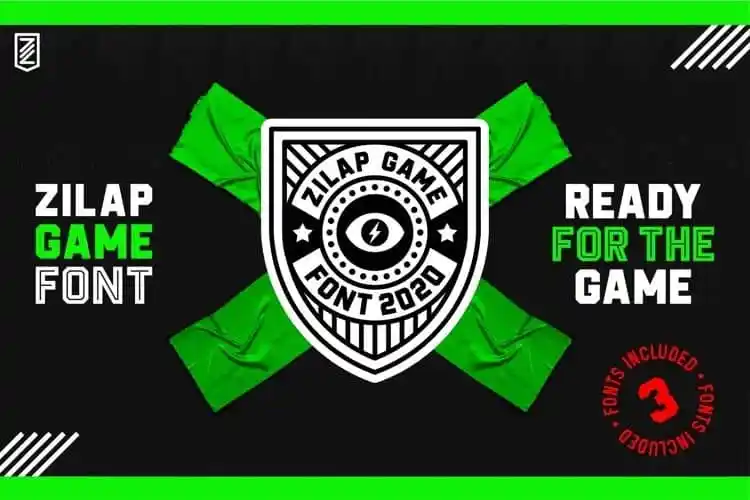
Zilap Game Display Font é uma fonte moderna do tipo sans-serif inspirada nos antigos fonts serif clássicos. Seu designer, LJ Design Studios, capturou a essência vibrante e dinâmica que se encontra nas artes digitais atuais, especialmente em jogos de esportes eletrônicos e esportes ao vivo. Esta fonte é projetada para representar tudo o que traz energia e movimento, ideal para criações visuais envolventes e criativas. Com uma disposição limpa e clara, Zilap Game Display Font oferece a liberdade de expressão necessária para qualquer tipo de projeto visual, seja ele em um site de jogos ou aplicativo esportivo, ou em qualquer outro ambiente que necessite de uma fonte poderosa e moderna. Seja na criação de banners promocionais, iconografia chamativa ou letras destacadas em vídeos, Zilap Game Display Font está preparada para capturar o seu público objetivo com a energia necessária para criar um impacto visual profundo.